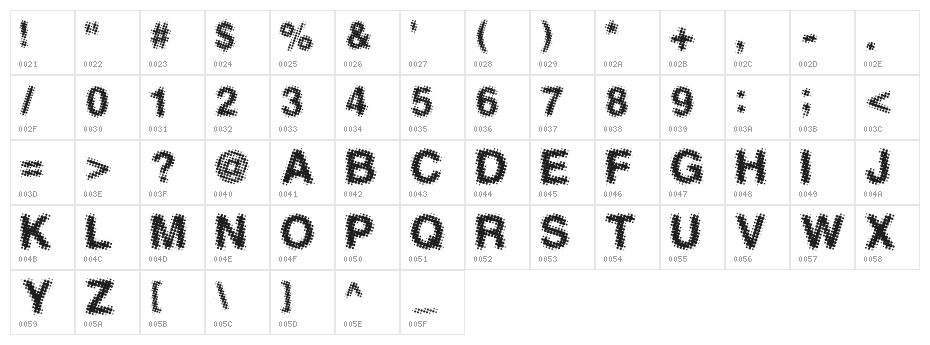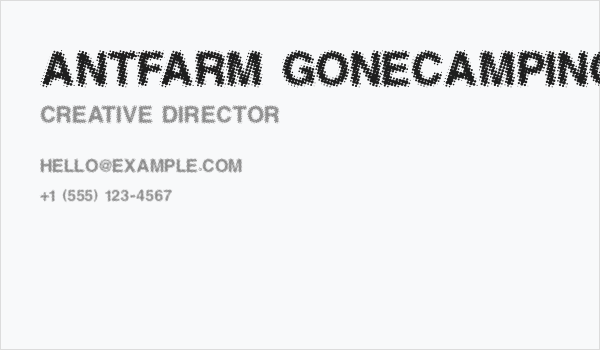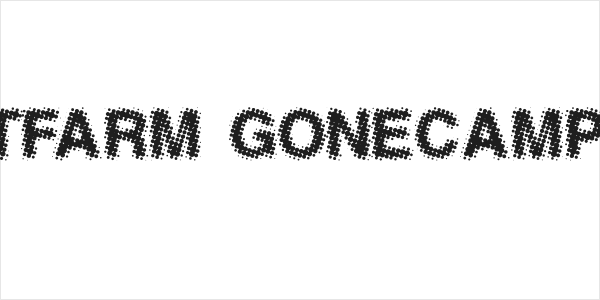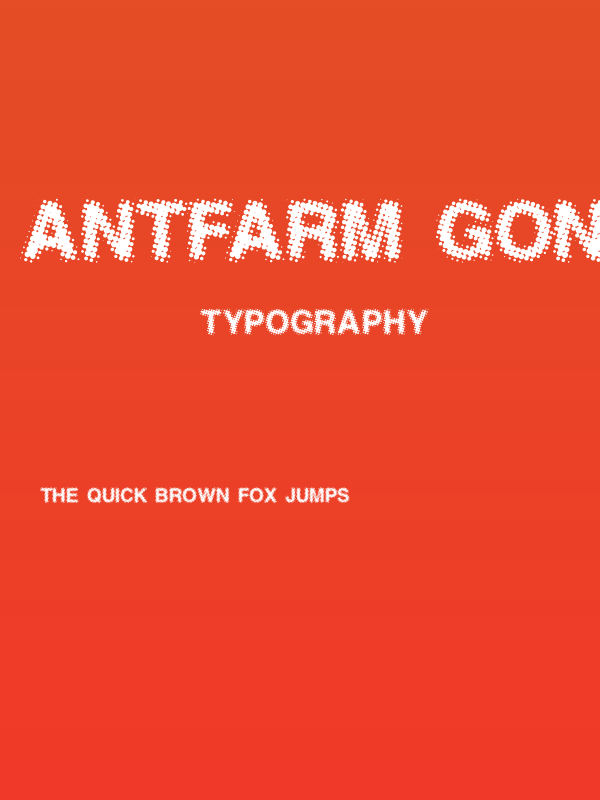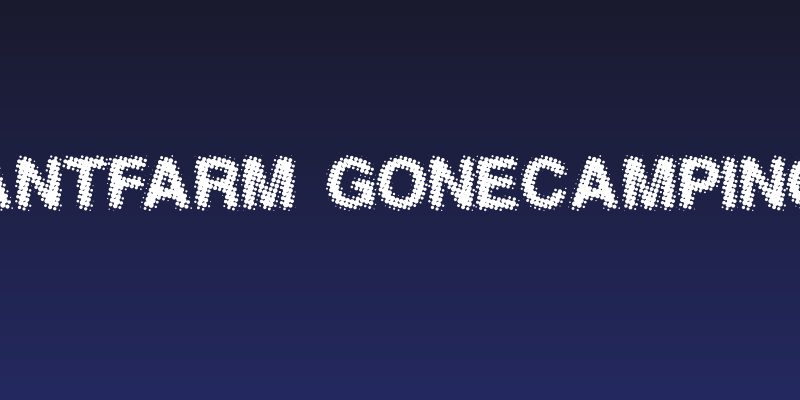
AntFarm GoneCamping Font
| Vorgeschlagene Projekte | Ideal for posters, advertisements, children's books, and creative design projects that require a fun and engaging typeface. |